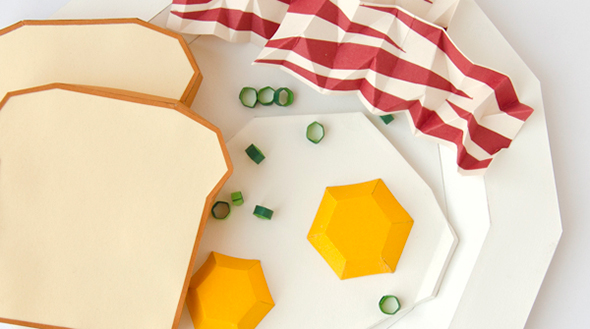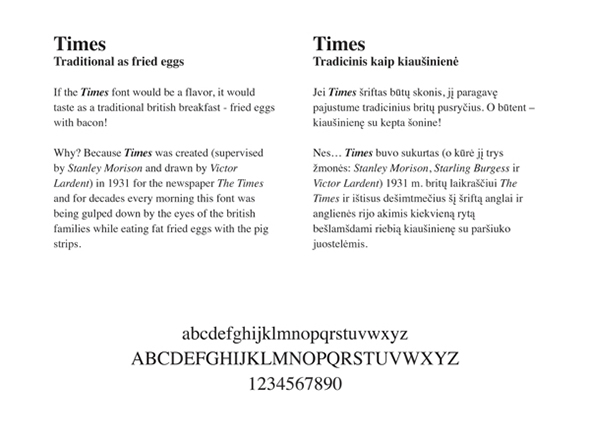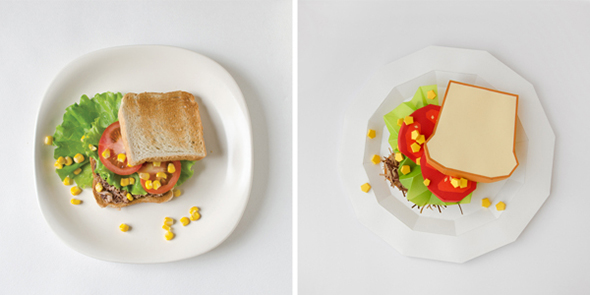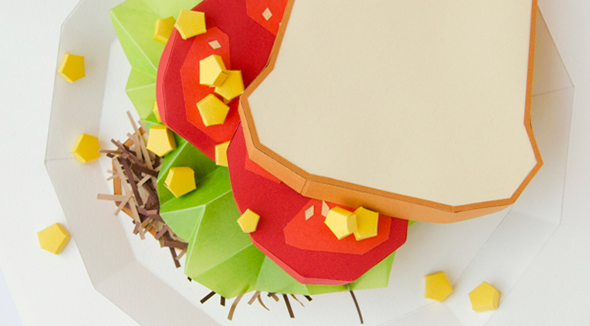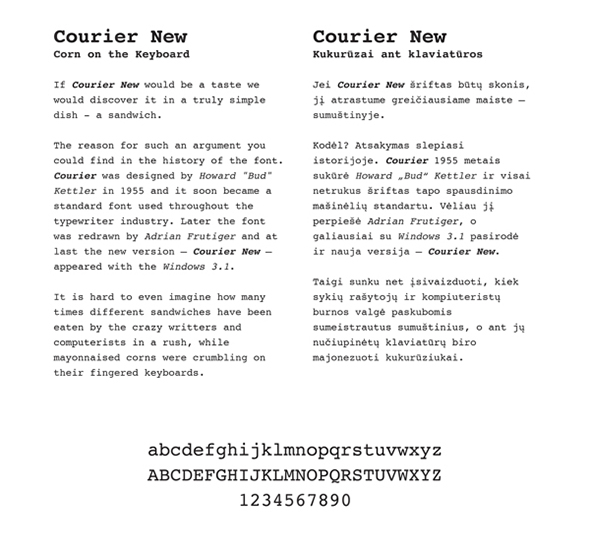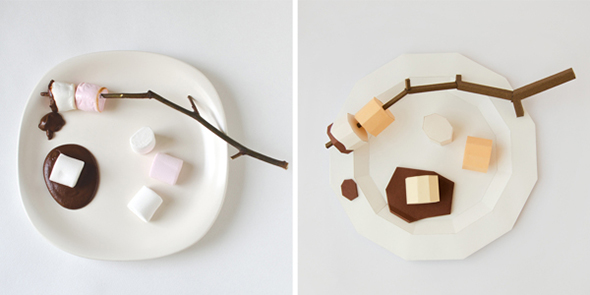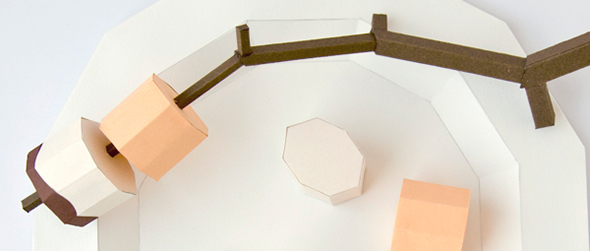
Taste The Font
Kotryna e Miglė sono giovani designer lituane. Tra i loro ultimi progetti c’è Taste the Font, presentato in occasione della Vilnius Design Week 2013. Tre pietanze ricreate con la carta ed abbinate ad altrettanti font: il Times, classico come una colazione all’inglese; il Courier, semplice come un buon sandwich; il Comic Sans, da evitare proprio come un grande chef eviterebbe di arrostire dei marshmallow!
Taste the Font